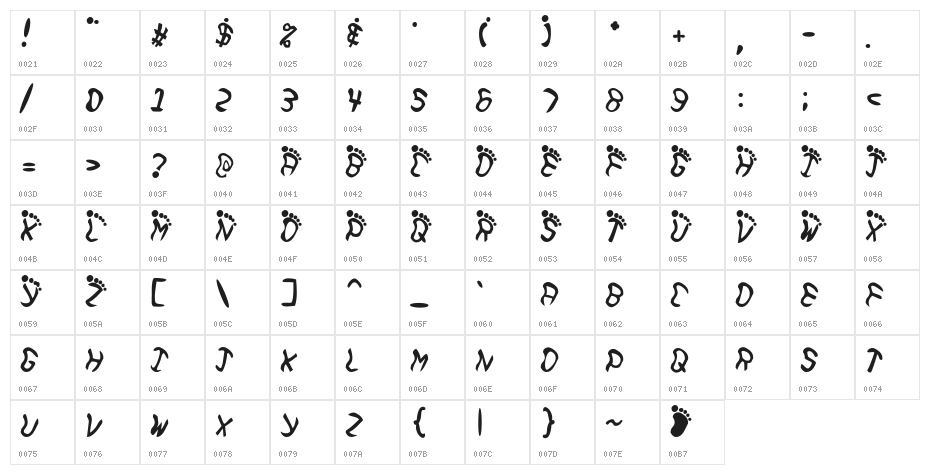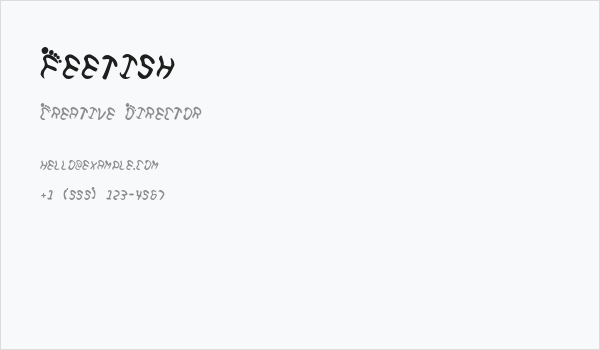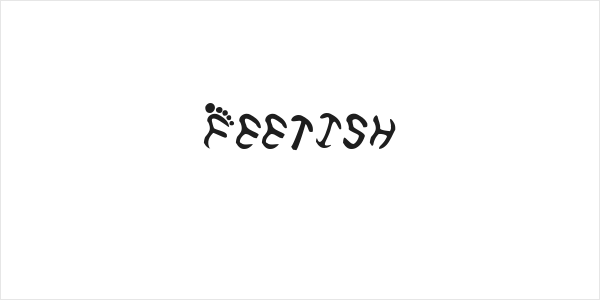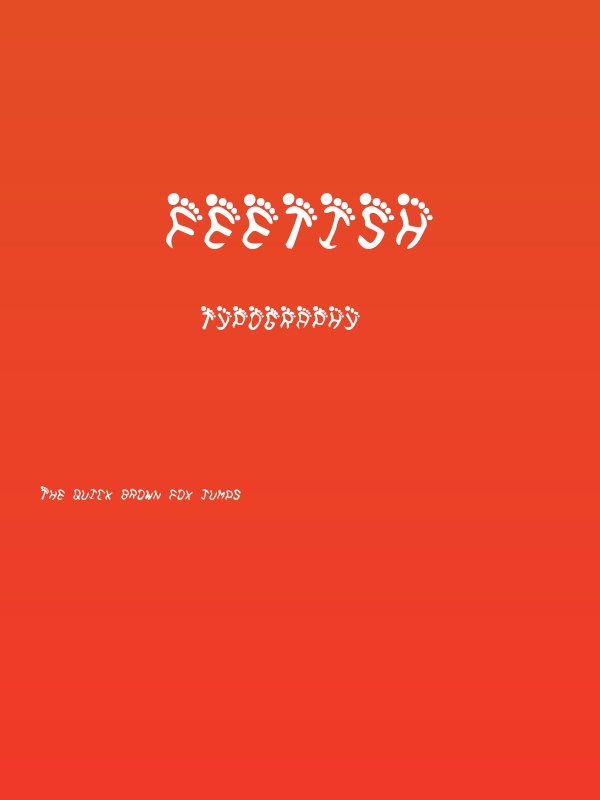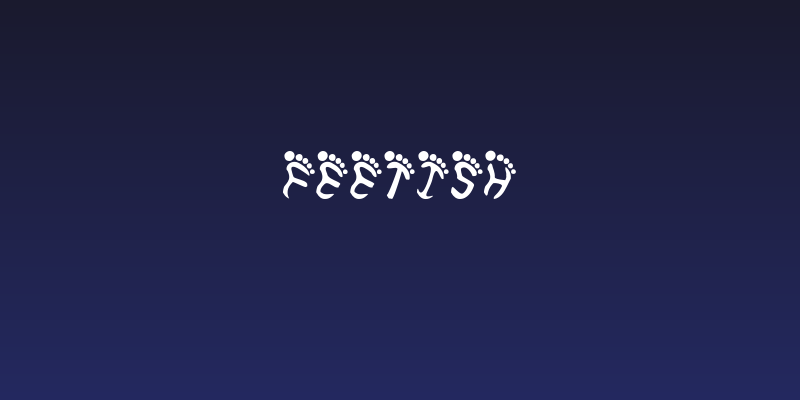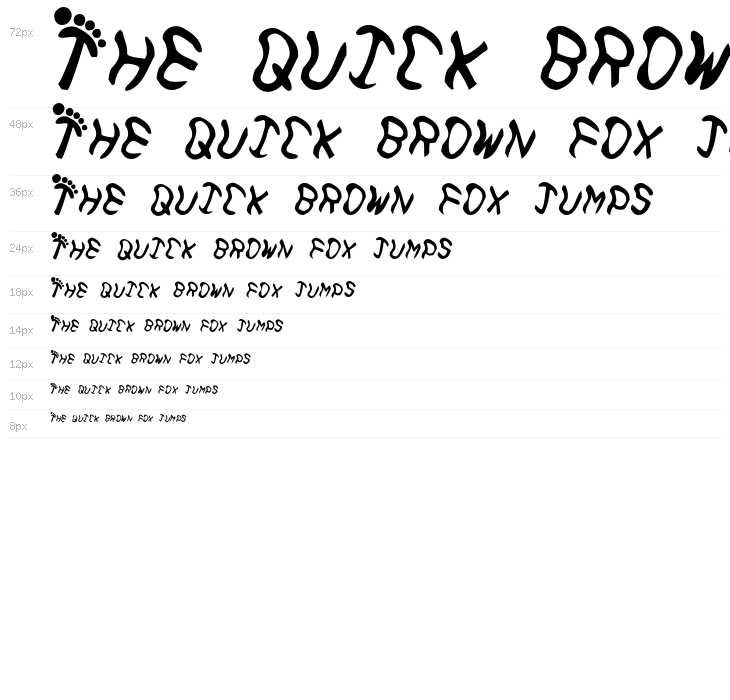
Feetish Font
✎ Decorative
| 分类 | Decorative |
| 整体风格 | Whimsical |
| 使用场景 | Logos, Headlines, Posters |
| 推荐项目 | Ideal for children's books, playful branding, party invitations, and creative posters. |